معرفی خطوط اسلامی- خط رقعه
خط رقعه(رقعی)
در طول تاریخ خوشنویسی هرگاه خطی شکل میگرفت، کاتبان در استفاده های بعدی تلاش میکردند با دخل و تصرف، شیوه هایی متنوع از آن خط ابداع کنند. یکی از این تغییرات، استخراج خطی مختصر به منظور استفاده در حوائج فوری و تند نویسی بود. تند نویسی یکی از محرکهای اصلی رواج و شکلگیری خطوط مختلف بودهاست. یکی از این خطوط، خط رقعه است. رقعه در لغت به معنای پاره و نامه است. خط رقعه با الهام از خطوط نسخ و دیوانی بهوجود آمده و هدف اصلی از وضع آن افزایش سرعت در نوشتن بودهاست. خاستگاه خط رقعه که فرم ساده شدۀ خط نسخ است، به ترکیه عثمانی باز میگردد. در منابع، سابقۀ تاریخی خط رقعه از نمونههای موجود قدیم که بهدست آمدهاست به سال ۸۸۶ ق میرسد و براساس اسناد موجود، خط رقعه بر صورت اولیۀ خود از زمان سلطان محمد فاتح پیدا شدهاست و در روزگار ممتازبک فرزند مصطفی افندی به سال ۱۲۵۵ ق در سراسر امپراتوری عثمانی معمول بودهاست.
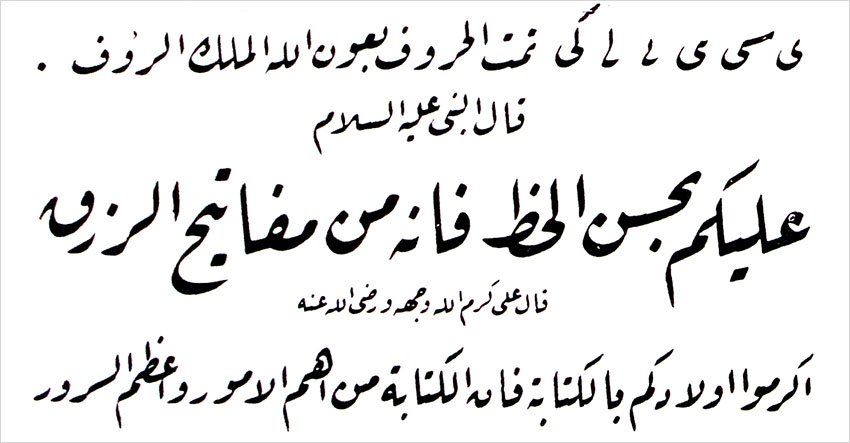
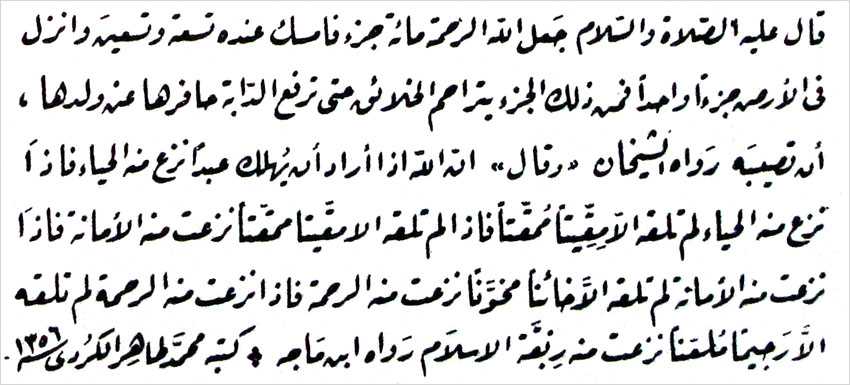
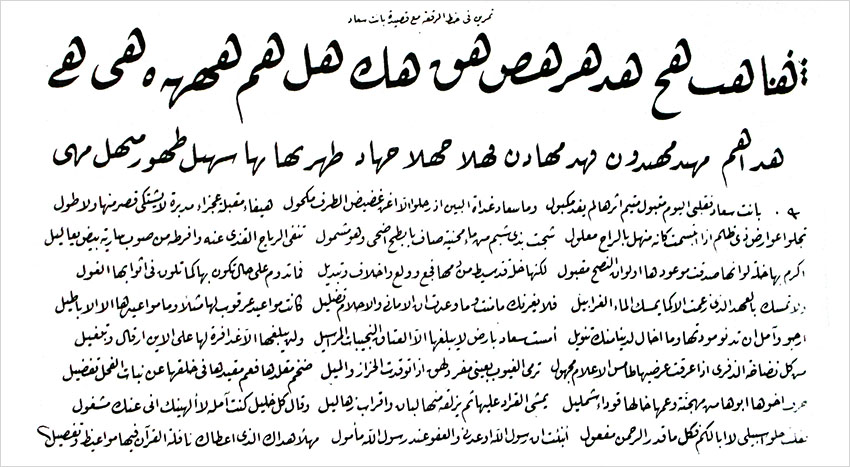
خط رقعه، شیوهای فربهتر از خط نسخ و کوتاهاندام و جمع و جور است و اندازۀ تنۀ اصلی حروف کوتاه قامت نوشته میشود. رقعه خطی واضح و روشن است و امروزه برای نوشتن عناوین کتابهای عربی کاربرد فراوانی دارد.
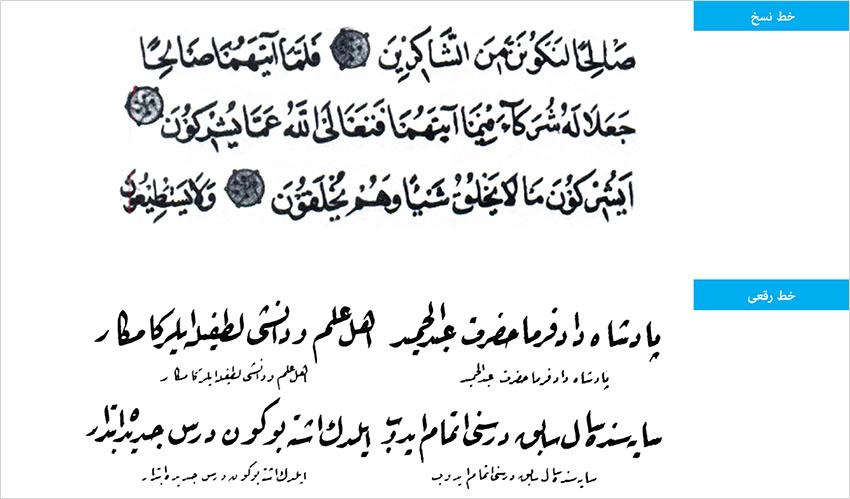
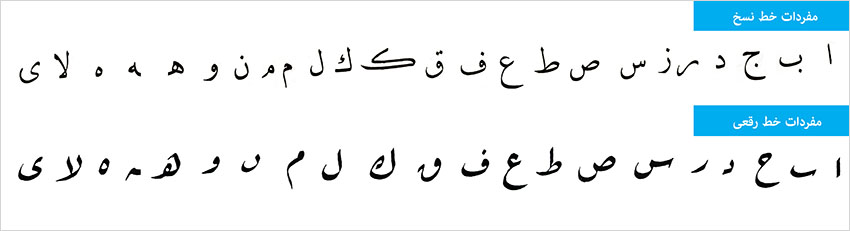
در خط رقعه از نسبتها و دانگهای میانی دم قلم کمتر استفاده شدهاست و بهویژه ظرافت کمتری در شروع و ختم حروف دیده میشود. الف با کمترین تنوع کتابت شده و شروع و ختم حروف با حداقل تنوع در قلمرانی نوشته شدهاست.
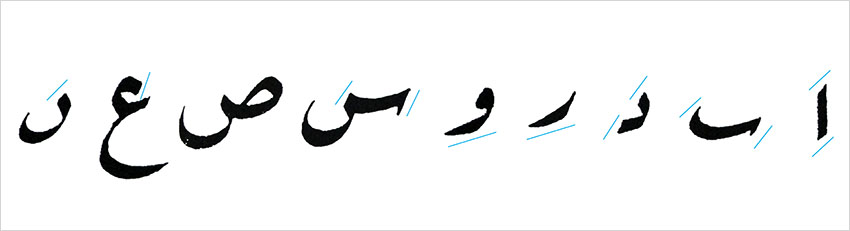
در خط رقعه، حرکات سطح بیشتر از دور حروف است. میزان سطح حروف سه برابر دور است.
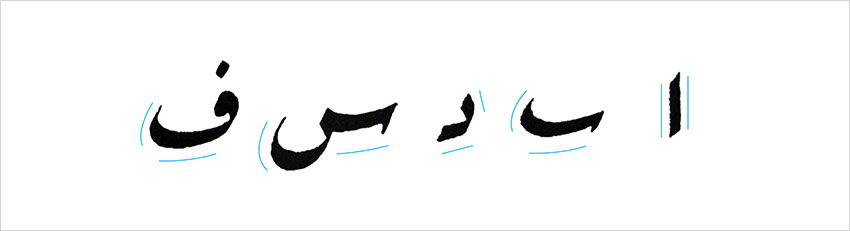
یکی دیگر از ویژگیهای خط رقعه، اشکال ترکیبی حروف است که احتمالا به دلیل سرعت در نوشتن به وجود آمدهاست.
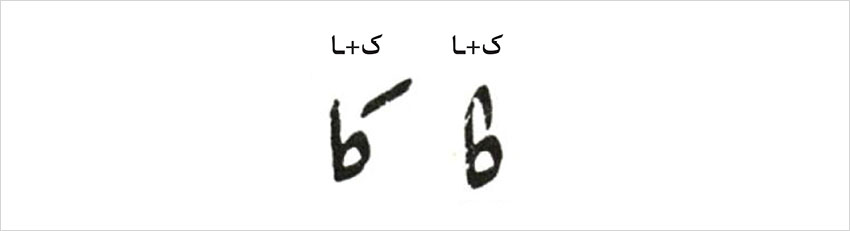
در خط رقعه، شروع حرف “هـ ” اغلب به شکل باز نوشته میشود.
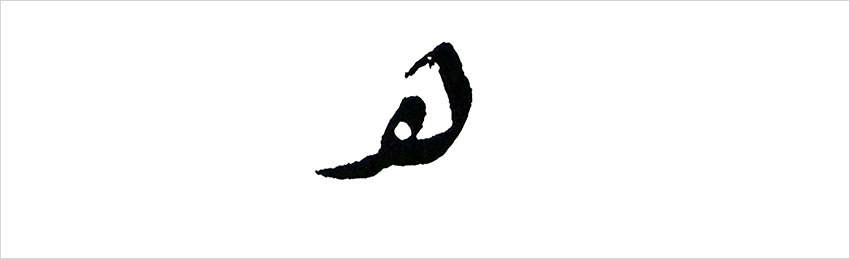
انتهای حرف “ق” با دنبالهای به سمت چپ برگشتهاست.
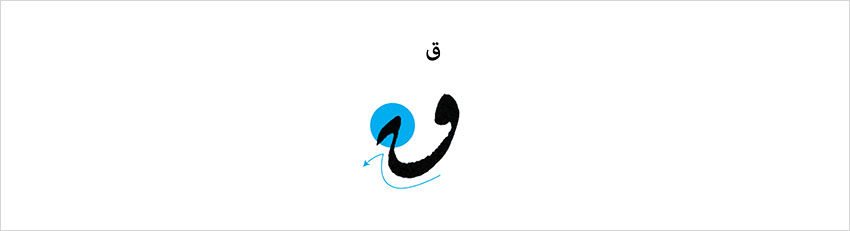
دو نقطهها و سه نقطهها بهشکل پیوسته کتابت میشود؛ خصوصیتی که احتمالا به دلیل سرعت در کتابت، تندنویسی و آسان نویسی ایجاد شدهاست.